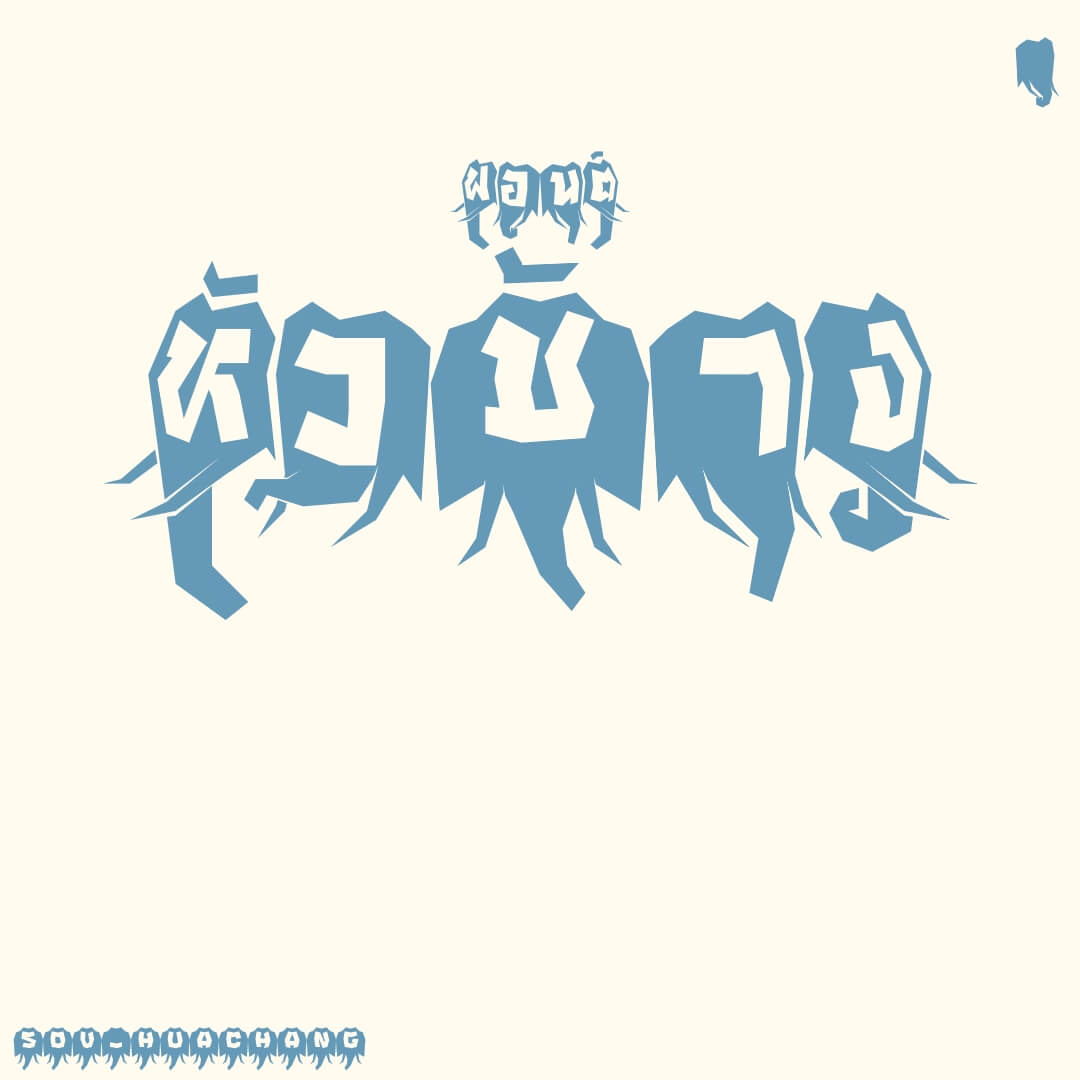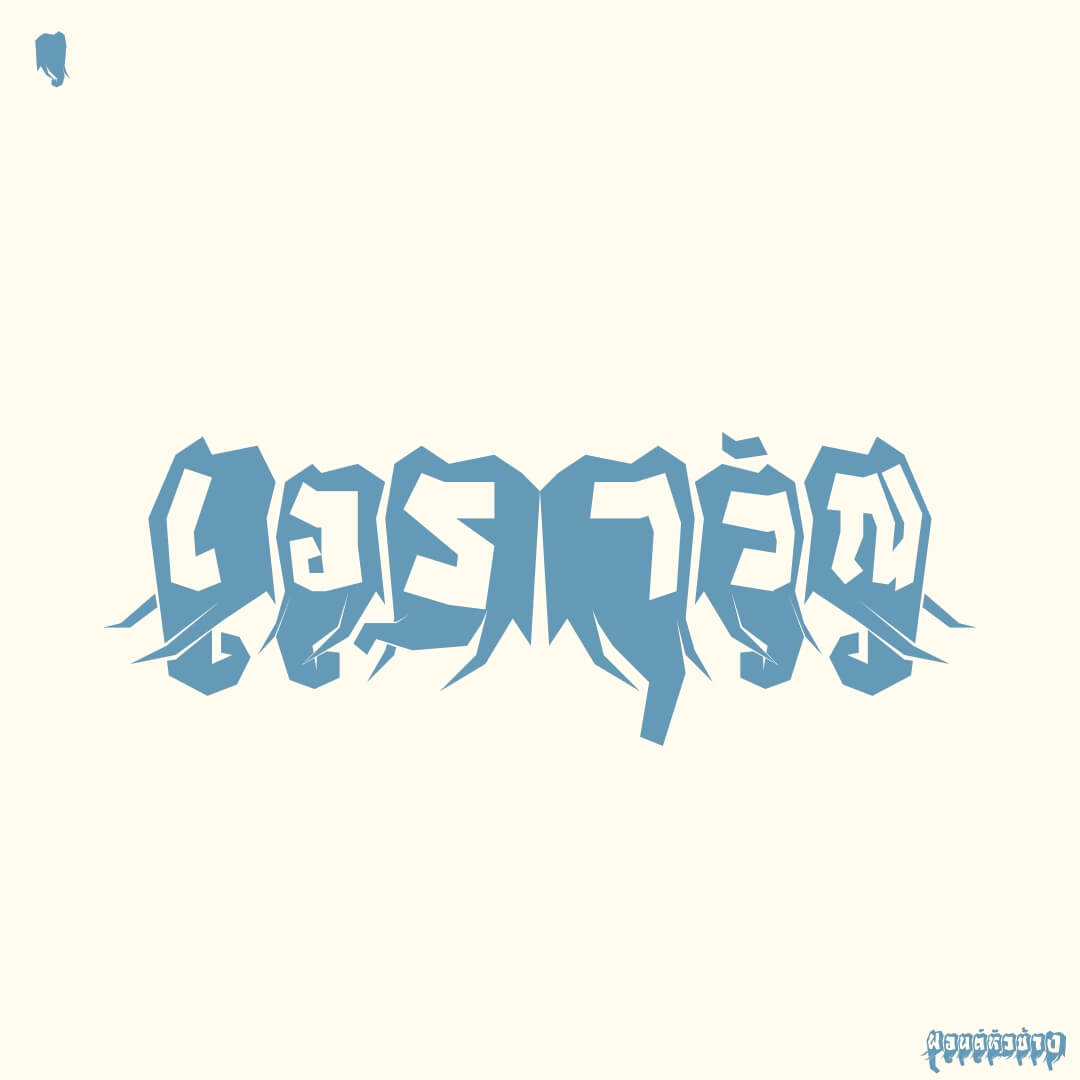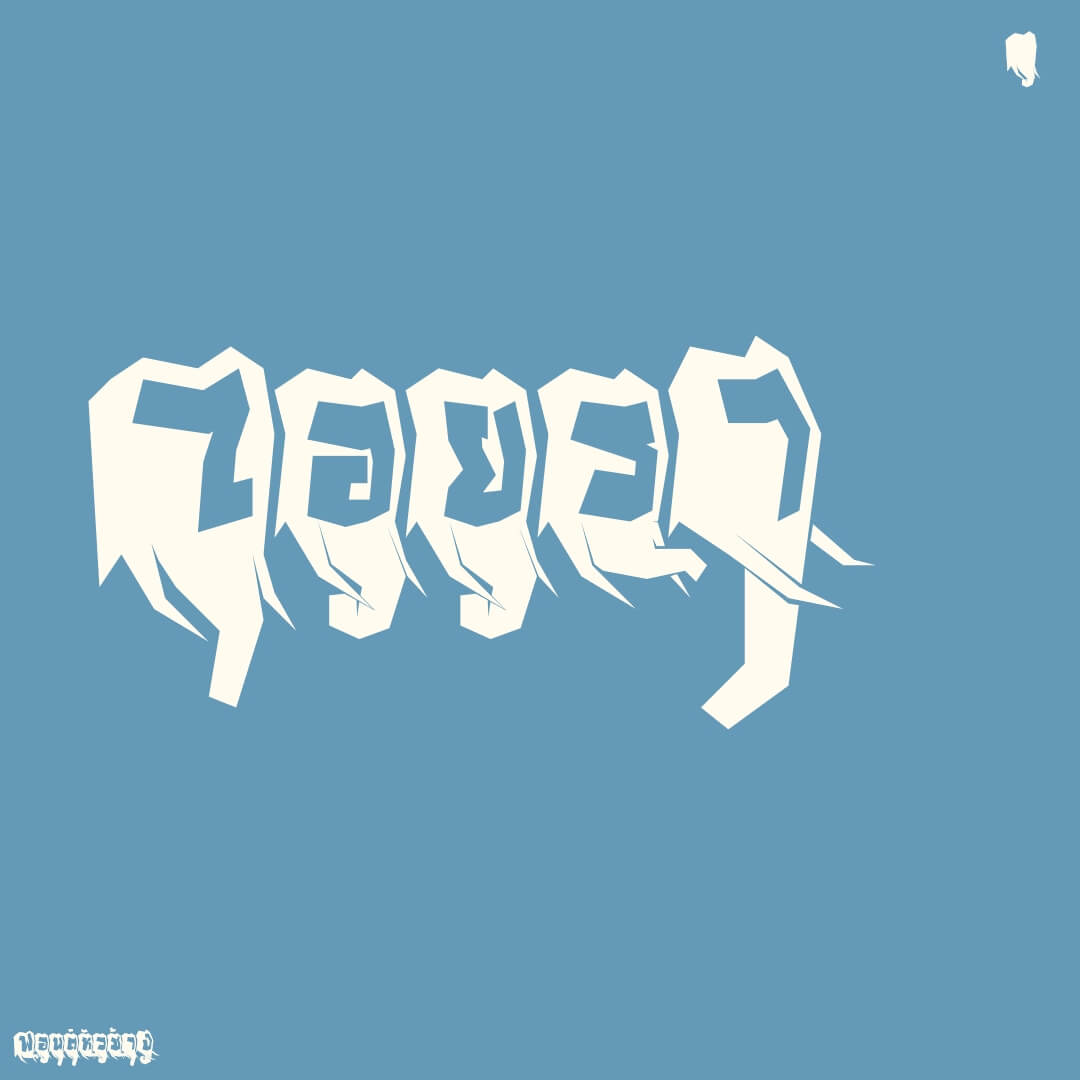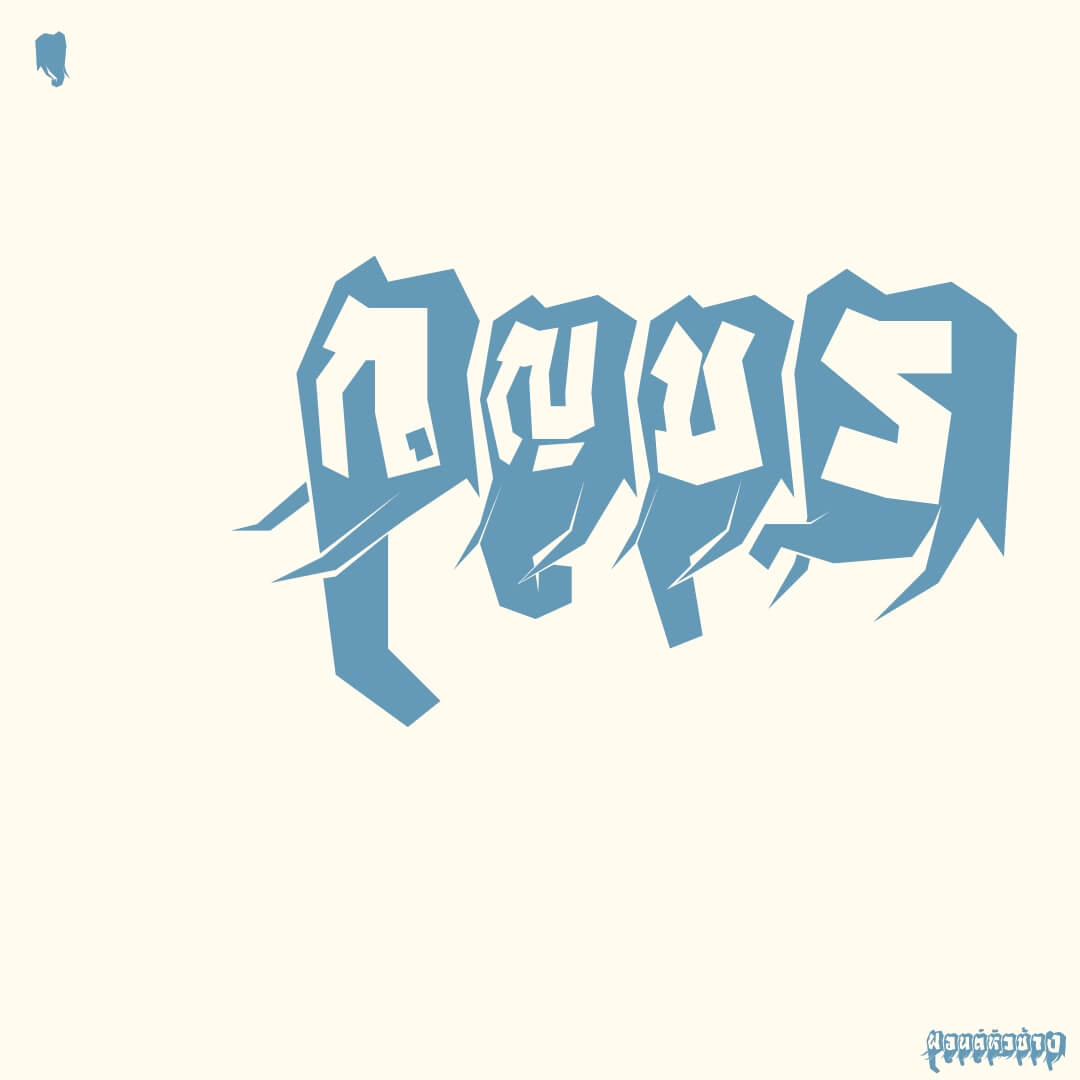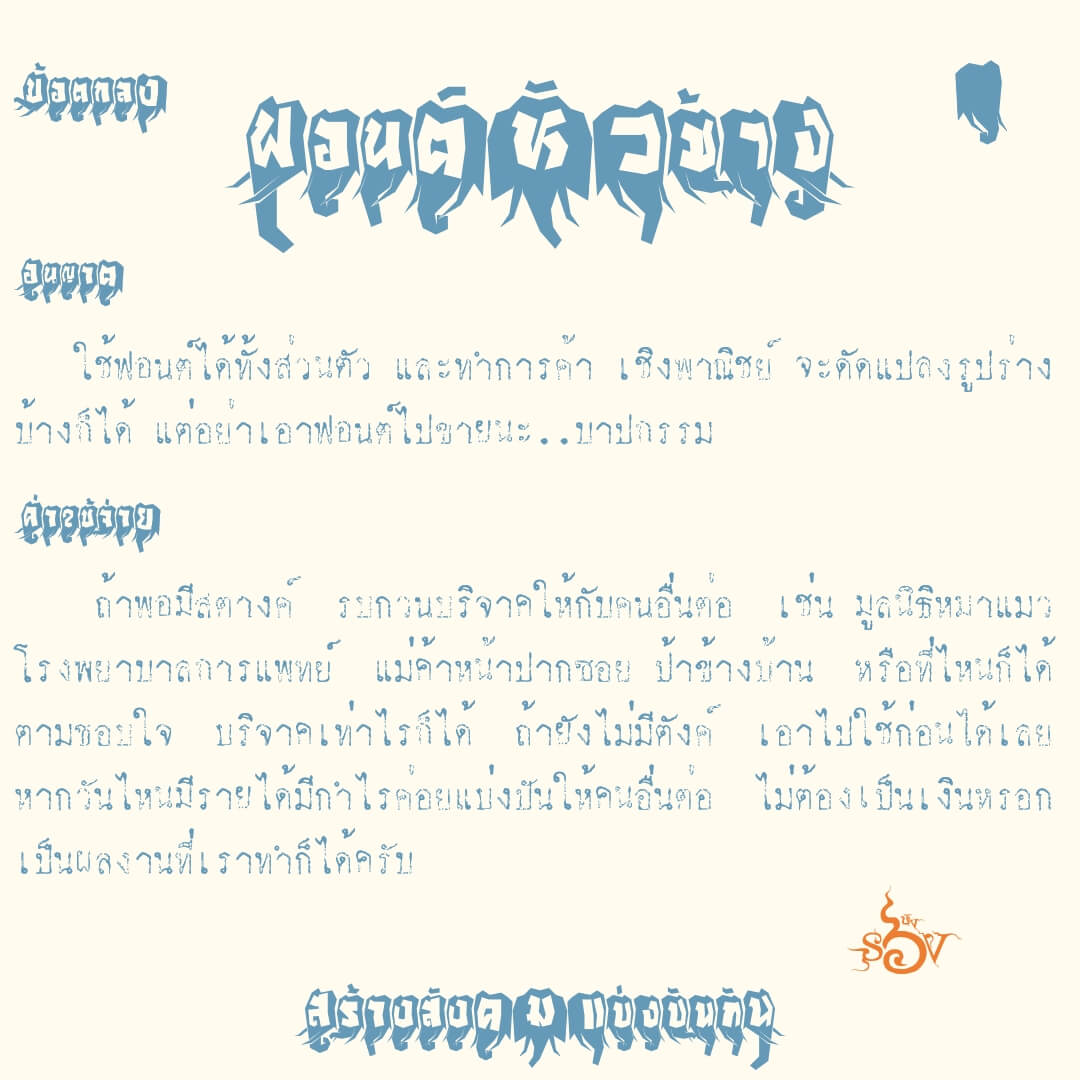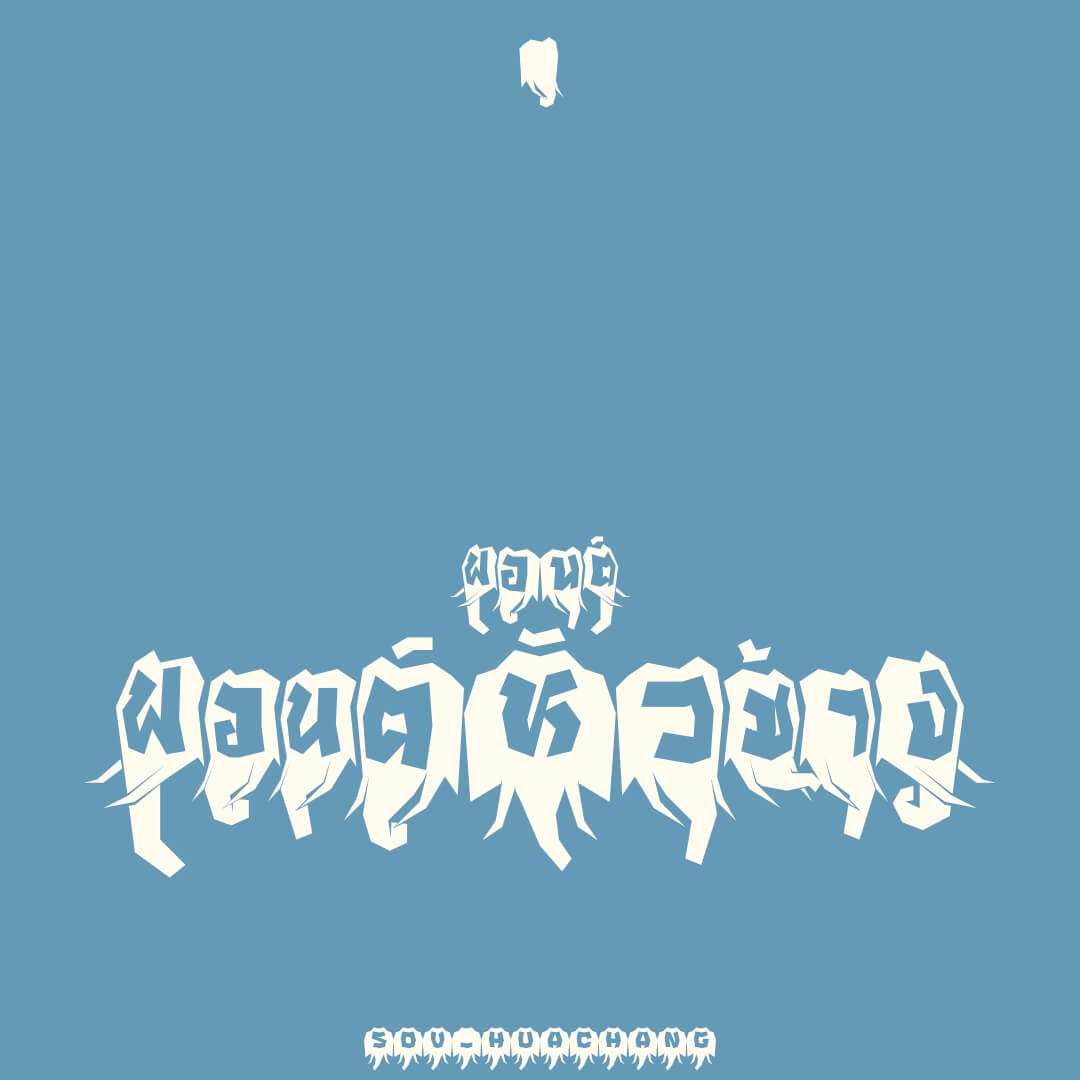
หัวช้าง (SOV_HuaChang)
3d animal experiment logo เหลี่ยม แข็งแรง
ฟอนต์หัวช้าง – ปรกติหันซ้าย กด bold หันขวา หน้าตรงใช้ ฯฯ นำหน้า
เบื้องหลังการออกแบบ : ฟอนต์ หัวช้าง